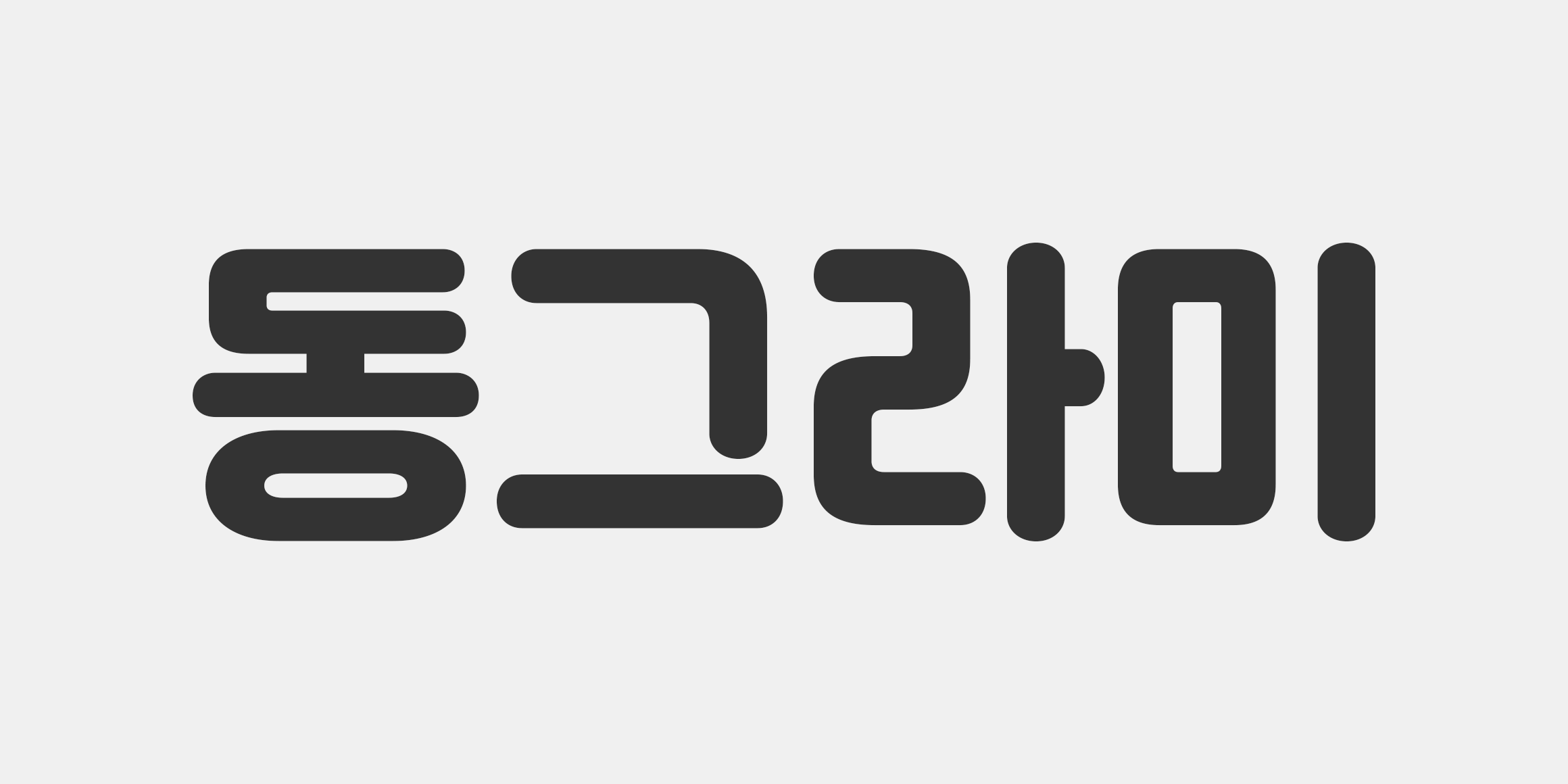
복고 컨셉이지만 디테일을 정교하게 다듬은 폰트로 어설픈 마감의 복고 폰트와는 다릅니다. 네모틀 가득 글자를 채워 여유 있는 속공간을 가지며, 단순하면서 재밌게 다듬어진 곡선과 둥글려진 획의 마무리가 특징적입니다.
총 9가지의 세분화된 두께를 제공하는데 중간 이하의 얇은 두께는 자막 용도나 준 본문용으로 활용이 가능하며 두꺼운 두께는 특징 있는 타이틀 용도로 쓰기에 적합합니다.